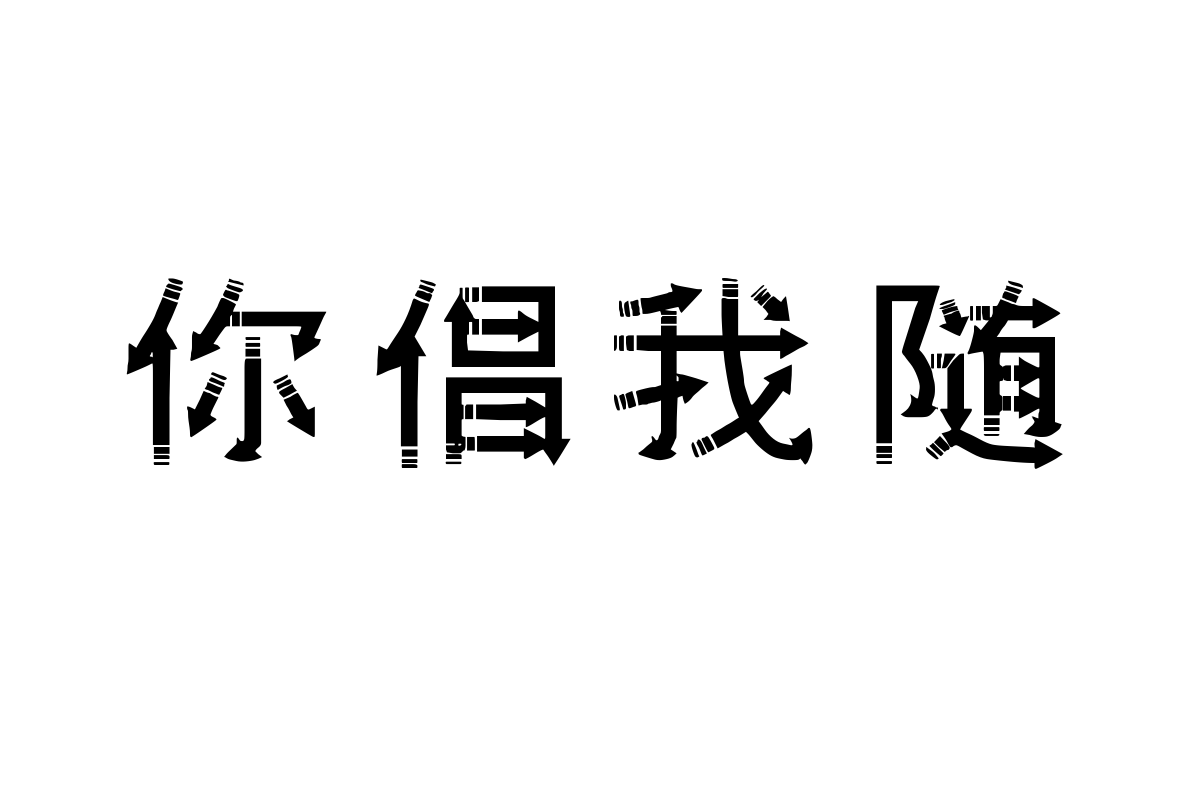
汉标–速度箭头体字体是一款专为速度和效率设计的专业字体。它以其独特的形状和结构,能够快速地传达出速度的概念,使文字更加生动有趣。这款字体适用于各种需要强调速度的场合,如广告、海报、宣传册等。
汉标–速度箭头体字体的特点如下:
1. 形状独特:这款字体采用了类似箭头的形状,使得文字在视觉上更加突出,能够迅速吸引人们的注意力。
2. 易于阅读:由于其独特的形状和结构,这款字体在阅读时不会产生任何困扰,使得文字信息更加清晰易懂。
3. 适用范围广泛:无论是在商业广告、体育赛事还是日常生活中,这款字体都能够很好地适应不同的场景,提高信息的传递效果。
4. 创意性强:汉标–速度箭头体字体不仅仅是一个普通的字体,它还可以根据需要进行定制和修改,满足不同用户的需求。
总之,汉标–速度箭头体字体是一款功能强大、适用范围广泛的专业字体,能够满足各种对速度有特殊要求的设计需求。